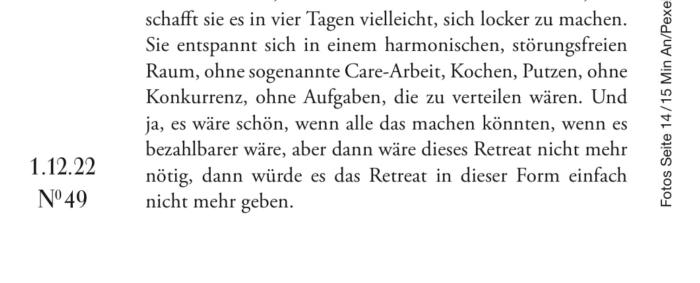
Buchsatz: Gedichte ohne Titel
Eine Herausforderung im Buchsatz:
Gedichte ohne Überschrift laufen manchmal auf die nächste Seite über. Deshalb ist nicht auf den ersten Blick erkennbar, ob dort ein neues Gedicht beginnt oder ob es die Fortsetzung ist.
Wie kann ich den Anfang eines neuen Gedichts dezent markieren? Initial, erstes Wort VERSAL oder gefettet sind ausgeschlossen.
Ich denke an ein kleines graues Quadrat am linken Seitenrand o. ä.
Einrücken oder ausrücken?
Vielleicht wäre eine Markierung mit einer Ellipse im Gedicht in einer neuen Zeile am Seitenende klarer, damit der Leser weiß, dass es weitergeht.
Wenn VERSAL ausgeschlossen ist, wird das vermutlich auch für Kapitälchen gelten, obwohl mir das am besten gefallen würde.
Man könnte den Abstand zum oberen Seitenrand variieren: In Romanen sieht man ja öfter, dass Kapitel, wenn sie grundsätzlich auf einer neuen Seite beginnen, mehr Abstand zum oberen Rand haben als die Folgeseiten mit normalem Text. Das würde bei Gedichten bedeuten, dass die meisten Seiten tiefer beginnen und nur bei einer Gedichtfortsetzung die erste Zeile wirklich am oberen Rand des Satzspiegels steht.
Oder man arbeitet mit einer Kopfzeile, wobei unterschiedliche Möglichkeiten denkbar wären: Lebender Kolumnentitel nur mit Linie auf der ersten Seite des Gedichts, Linie und Gedichttitel auf der Folgeseite. Oder nur Linie auf Folgeseite. Oder umgekehrt.
Oder man markiert auf der ersten Seite unten irgendwie, dass es weitergeht.
Ich würde wohl nicht markieren, dass es weitergeht, sondern Anfang oder Ende von jedem Gedicht markieren.
... oder eine dünne, randläufige Linie :-?
In den Ausgaben antiker Gedichte sind die Zeilen in Fünfer-Schritten nummeriert und die Zählung fängt bei jedem Gedicht neu an. Soll die Lyrik die Zeiten überdauern oder gar Gegenstand des Schulunterrichts werden, dann hilft die Zeilenzählung enorm bei der Zitierbarkeit.
Die Zeilenzählung hat ihre Berechtigung zum Beispiel in den von Dir genannten Fällen. Aber in einem normalen Gedichtband würde mich das doch sehr stören.
So habe ich es mal in der Vergangenheit umgesetzt: Gedichte enden mit einem eckigen Punkt; die übrige Interpunktion ist rund. Doch wahrscheinlich ist das keinem Leser wirklich aufgefallen. Es war wohl doch zu dezent.
Ein bisschen weniger subtil sollte es vielleicht doch sein ;-)
Ich bin regelmäßig irritiert, dass das Ende der Texte im Zeit-Magazin mit dem Datum – irgendwo auf der Seite – enden. Weil sie in der Regel die Kolumnen komplett füllen, will ich immer auf der nächsten Seite weiterlesen.
Ist jetzt keine Lyrik, macht das Problem aber deutlich, wenn’s mal nicht deutlich ist
Sehr wahrscheinlich werde ich nun Anfang UND Ende markieren. Was verstehen Sie unter einer randläufigen Linie?
Vielleicht das Alinea-Zeichen am Ende?
Könnte auch gut aussehen. Vielleicht nicht grad das Kapitelzeichen, sondern eher eine Englische oder andere Schmucklinie als Texttrenner.
Ein bisschen weniger subtil sollte es vielleicht doch sein